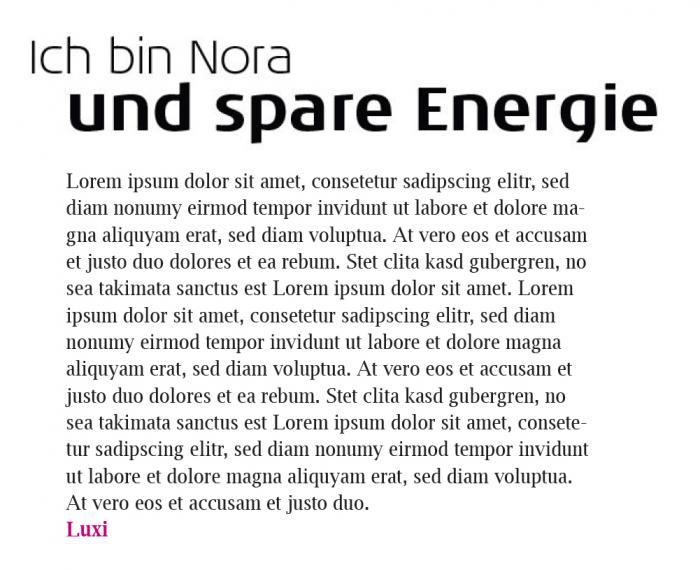
NOA – begleitender Font für Fließtext
ich lese schon länger mit und behaupte, Ihr seit zumTeil für meine typografische Bildung mitverantwortlich.
Ich möchte die Noa für eine Besuchermesse einsetzen (Logo und Überschriften), die das Thema Energiesparen hat. Also Solar, Wind, regenerative Energie im Allgemeinen.
Ich bin der Meinung sie passt sehr gut, da sie nicht futuristisch, aber dennoch einen Hinweis auf die Zukunft enthält.
Sie ist natürlich etwas technisch, aber nicht so sehr wie die übrigen spornlosen, wie die Francker z.B. Ein wenig wäme strahlt sie auch aus, durch die runden Formen.
Da bei einigen Buchstaben (g, f) "gespart" wurde, wird das Thema irgendwie gut transportiert.
Nun suche ich eine Schrift, die ich für Kataloge oder Broschüren als Mengentext im Infoteil einsetzen kann, die sie harmonisch begleitet, modern aber nicht technisch oder kalt wirkt, denn es geht immer noch um Menschen im Kontext zu Technologie.
Generell habe ich mich bereits für eine Antiqua festgelegt.
Mir geistern Namen wie Minion, Frutiger Serif, Meta Serif im Kopf herum, würde da aber gerne eure feinfühlige Meinung dazu einholen.
Nagut,
die Frage ist vielleicht kompliziert gestellt.
Zuerst: das ist kein kommerzielles Projekt.
Was haltet Ihr von der Meta Serif zu der Noa? Gibt es Gründe, dass nicht zu machen?
Beide haben ja eine hohe x-Höhe und ich mag die Meta Serif, sie ist irgendwie erhaben und macht einen sehr sauberen Eindruck ..
Hallo Jakob,
die Frage ist schon gut verständlich, allerdings hat sie es inhaltlich in sich. Die Noa, die Du Dir ausgesucht hast, ist ja ganz schön eigenwillig - es ist nicht so einfach, da ad hoc den passenden serifenbehafteten Antagonisten zu finden. Spontan würde ich zu einer Slabserif-Schrift greifen, weil ich vermute, dass zartere Serifen nicht mit den plakativen und robusten Formen der Noa harmonieren.
Schau Dir doch auch noch mal die PMN Caecilia an oder die Sanchez. Die sind beide noch ein bisschen stabiler als die Meta Serif. Die Foro von Hoftype könnte auch interessant sein.
Ja, ich habe die Noa genau deswegen ausgesucht.
Etwas neutrales als Begleitung ist darum mein gedanklicher Ansatz.
Eine Slab hatte ich bisher gar nicht auf dem Zettel, danke für die Anregung, dass werde ich sofort ausprobieren.
Das einzige was ich befürchte ist das, wenn ich zwei eher ungewöhnliche Fonts kombiniere, die Aufmerksamkeit zu sehr an der Schrift hängen bleibt.
Deine Tipps gefallen mir sehr.
Ich teste.
Warum nicht? Gute Slabserifschriften sind sorgfältig gesetzt ohne weiteres fließtexttauglich. Das habe ich gerade mit der FS Clerkenwell durchgespielt und bin vom Ergebnis sehr angetan.  :-)
Weiß ich auch nicht, rein intuitiv. Wahrscheinlich weil ungewohnt.
Also das war ein guter Tipp von dir, ich denke damit kann man gut leben.
Foro links, Meta rechts. Die Anderen habe ich leider nicht.
Ist jetzt nicht schön gesetzt, aber ich finde die Foro und die Noa gehen gut zusammen, wenn der Größenunterschied stark genug ist.
Spritzig, fresh, anders, markant.
Falls keine Einwände kommen, und ich morgen immer noch ein gutes Gefühl habe, wirds das werden.
Ich hoffe, dass ich ein gutes Händchen fürs setzen habe.
Gefällt mir beides gut! Die Foro ist der Noa von den Buchstabenproportionen noch etwas ähnlicher, hat eine etwas höhere x-Höhe. Ich würde ihr daher noch etwas mehr Zeilendurchschuss geben - so dass der luftige Eindruck entsteht, den Du bei der Meta schon erreicht hast.
In Ordnung. Ich bin ganz verzaubert von dieser guten Lösung und der netten Hilfe.
Ich zeige später wie es fertig aussieht und frage nochmal nach, falls ich unsicher werde.
Melde Dich gerne wieder, ich bin gespannt, wie das Resultat aussehen wird.
Ich schließe mich einfach mal Kathrin an, die Foro finde ich die bessere weil harmonischere Kombination. Fein fein!
PS.: Musste heute Nachmittag die Frage auch erst einmal setzten lassen. Übrigens hat mich die Noa etwas an die dänische FF Max erinnert, welche mittlerweile auch eine Slabschwester bekommen hat, aber ob diese im Mengensatz dann auch so gut funktioniert wie die Foro, steht auf einem anderen Blatt … nur so am Rande. : )
Hi R::bert,
danke für die Bestätigung!
Die Max ist ja auch pikfein, die muss ich mir merken. Ist allerdings recht quadratisch, und das kleine g ist nicht so "catchy".
Dafür hat sie lustige Schlenker am Fuß :) Sehr lecker.
Ich kann eine Slab Version nicht finden, meinst du vielleicht die FF Unit Slab? Die hab ich auch auf dem Zettel, läuft mir aber zu schmal.
Ich würde Buchstaben nicht mit zu viel Bedeutung aufladen wollen, das wird in der Regel keiner mitbekommen. Buchstabenformen können das gar nicht leisten. Das wäre eine Aufgabe fürs gesamte Design — Farben, Formen, Proportionen und so weiter.
Die Luxi bitte nicht als ausgearbeiteten Vorschlag verstehen, da gibt es sicher zig bessere.
Ja klar, wenn überhaupt dann halt unterschwellig, wie ein leichtes Aroma in der Suppe.
Aber es ist doch immer gut wenn man die Wahl irgendwie Begründen kann, selbst wenns keiner mitkriegt.